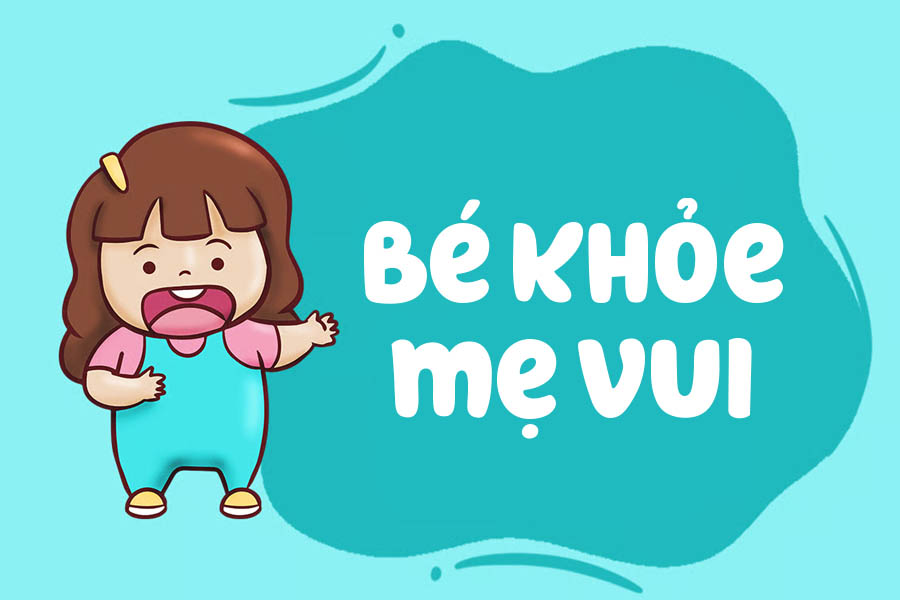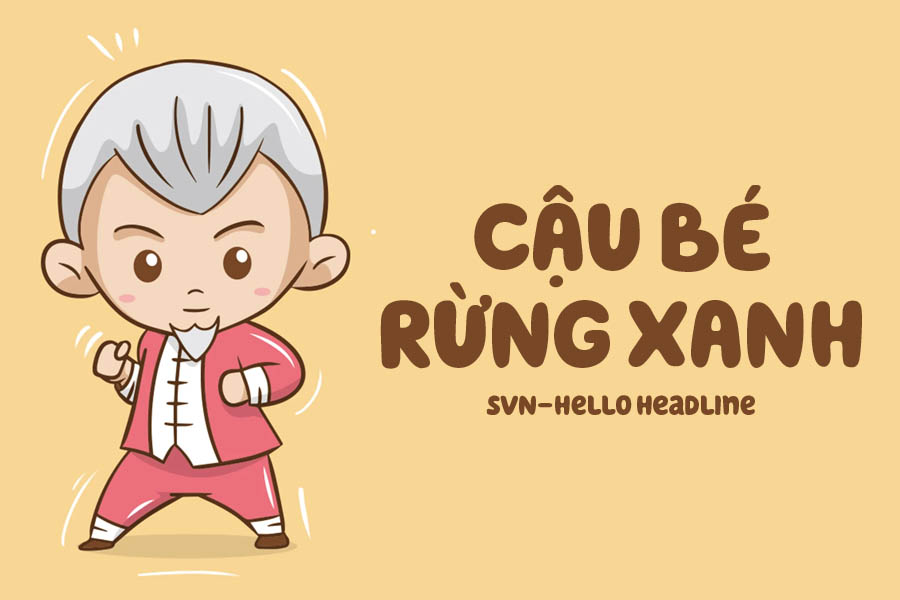
Tác giả Sarid Ezra
Việt hóa Team SVN
Bạn đang tìm kiếm một font chữ ngộ nghĩnh, vui nhộn và thân thiện với trẻ em? Font SVN-Hello Headline chính là lựa chọn lý tưởng cho các thiết kế mang phong cách hoạt hình, giáo dục và sản phẩm dành cho thiếu nhi. Với nét chữ tròn trịa, mềm mại và hỗ trợ tiếng Việt đầy đủ, font này sẽ thổi hồn tươi mới vào mọi dự án thiết kế sáng tạo của bạn.
Điểm nổi bật của font chữ SVN-Hello Headline
Font chữ SVN-Hello Headline gây ấn tượng nhờ kiểu dáng béo tròn, bo cong nhẹ nhàng. Mỗi chữ cái được tạo hình với nét uốn mềm mại, khiến tổng thể font trở nên vui tươi, ấm áp và cực kỳ dễ mến. Đây là phong cách lý tưởng cho các thiết kế hướng tới trẻ em – từ bìa sách thiếu nhi, tranh truyện đến các poster lớp học.
Một điểm mạnh không thể bỏ qua của font này là độ dày đồng đều và khả năng đọc tốt, ngay cả ở cỡ chữ lớn dùng trong tiêu đề hay băng rôn. Nhờ đó, SVN-Hello Headline trở thành lựa chọn lý tưởng cho các bảng tên lớp, banner trường mầm non, sách vải tương tác hay các sản phẩm đồ chơi học tập. Dù ở môi trường in ấn hay kỹ thuật số, font vẫn giữ được sự rõ ràng, thu hút ánh nhìn.
Đặc biệt, font hỗ trợ đầy đủ tiếng Việt, với hệ thống dấu câu được thiết kế trau chuốt, căn chỉnh đẹp mắt và không bị lỗi ký tự. Điều này giúp người dùng yên tâm sử dụng trong các tài liệu giáo dục tiếng Việt mà không cần chỉnh sửa thêm.
Cuối cùng, thiết kế của SVN-Hello Headline đã được tối ưu để phục vụ trẻ em: các chữ cái có chiều cao tương đồng, bố cục không nặng nề, giúp trẻ dễ đọc và phân biệt mặt chữ. So với nhiều font sans-serif thông thường, kiểu chữ này thân thiện hơn nhiều với thị giác và nhận thức thị giác của bé.
Font chữ lý tưởng cho:
• Biển bảng trường học, lớp mầm non, nhà trẻ
• Học liệu Montessori, sách tô màu, sticker
• Bao bì sản phẩm cho bé: bánh ăn dặm, sữa, đồ chơi
• Poster, banner khu vui chơi, sự kiện thiếu nhi
• Ấn phẩm thương hiệu dành cho ngành hàng trẻ em
Thông tin kỹ thuật:
• Tên font: SVN-Hello Headline
• Thể loại: Font chữ béo tròn – sans serif hoạt hình
• Việt hóa bởi: Nhóm SVN Fonts
• Tác giả gốc: Sarid Ezr